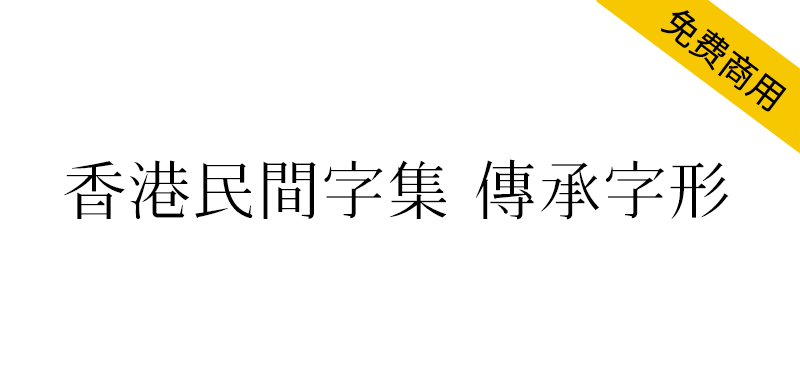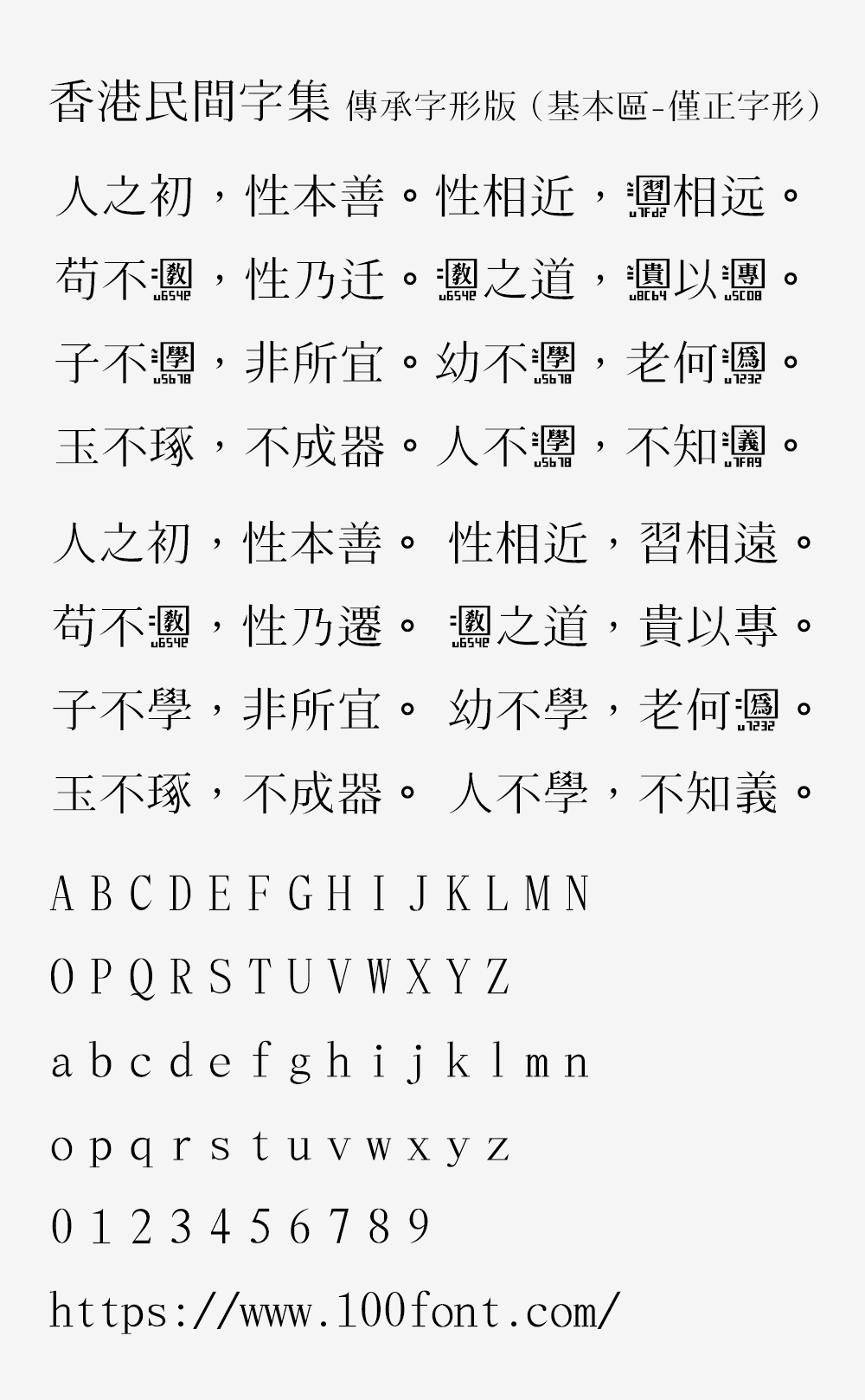
香港民间字集计划(Hong Kong Character Set Project,简称HKCS)是一项致力于整理古今汉字字形、并以明朝体(宋体)风格制作字体库的民间项目。
香港民间字集 传承字形版 (基本区-仅正字形)是一款衬线字体,严格遵循@SyaoranHinata提出的传统字形规范,所选字形均符合现代甲骨文、金文和小篆字源学研究标准。
字符覆盖范围:基本区(URO/URO+)全部汉字、扩展A/B区部分粤语用字(香港地区适用),注:扩展A区完整支持正在开发中
异体字处理原则:对重复字形、简体字、俗写字及讹误字形等非标准变体,均通过视觉映射统一规范至正字形。
Hong Kong Character Set Project (HKCS) 香港民間字集 is a project to create fonts cataloguing modern and historical Chinese character glyphs in the Ming typeface.
HKCS Traditional Orthography (BMP-CanonicalOnly),A serif font that supports the traditional orthography according to the orthography outlined by@SyaoranHinata. The traditional orthography choosen is the one which matches modern Oracle Bone, Bronze Inscriptions and Small Seal etymology study better.
Character Coverage:This version of the font includes all characters in URO / URO+ and also select characters from Extension A/B for Cantonese support in Hong Kong. Full Extension A support is being worked on.
Treatment of Character Variants:Characters and glyphs which are deemed to be duplicates, simplified forms, vulgar forms or error glyphs are visually aliased to their canonical forms.